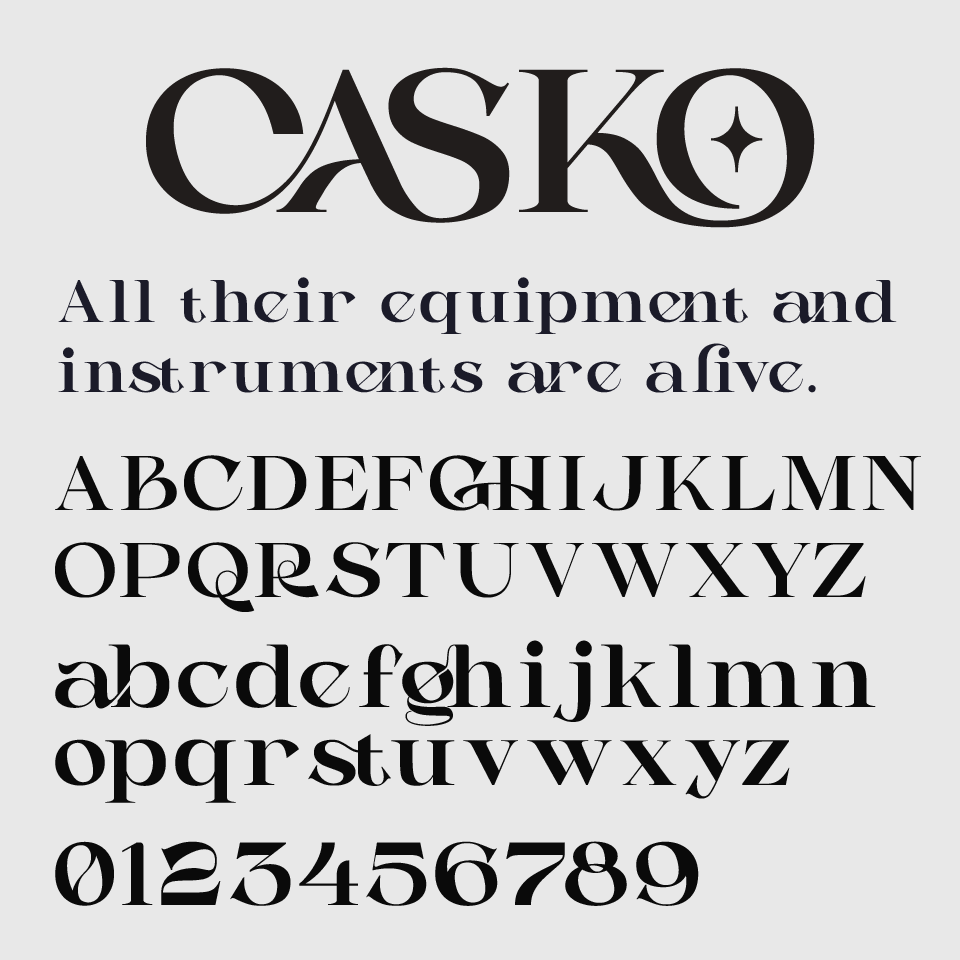
Caskoフォントは、装飾性と優美さを兼ね備えたセリフ体フォントです。
流れるようなカーブや尖ったセリフが目を引き、クラシカルな雰囲気と洗練されたムードを持ち合わせています。大文字の形状にはエレガントな遊び心があり、ロゴやタイトル用途に向いています。
文字の一部がユニークなリガチャが用意されたり、左右非対称な曲線が取り入れられていたりと、視覚的な仕掛けが随所に光ります。ファッションやコスメ、ラグジュアリー系ブランドとの相性が良く、記憶に残るビジュアル作りに活躍するフォントです。